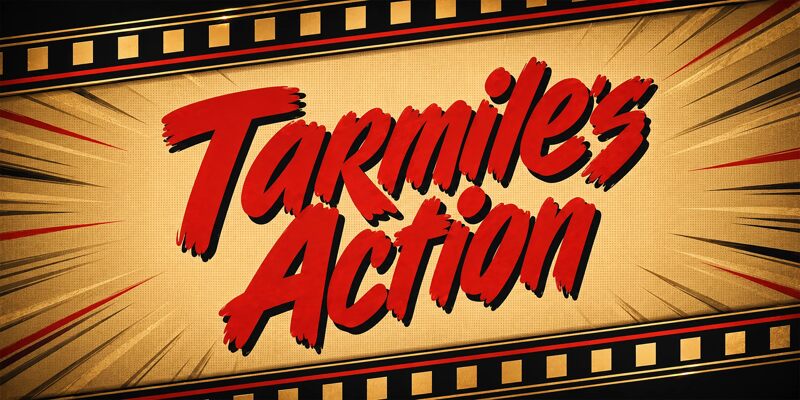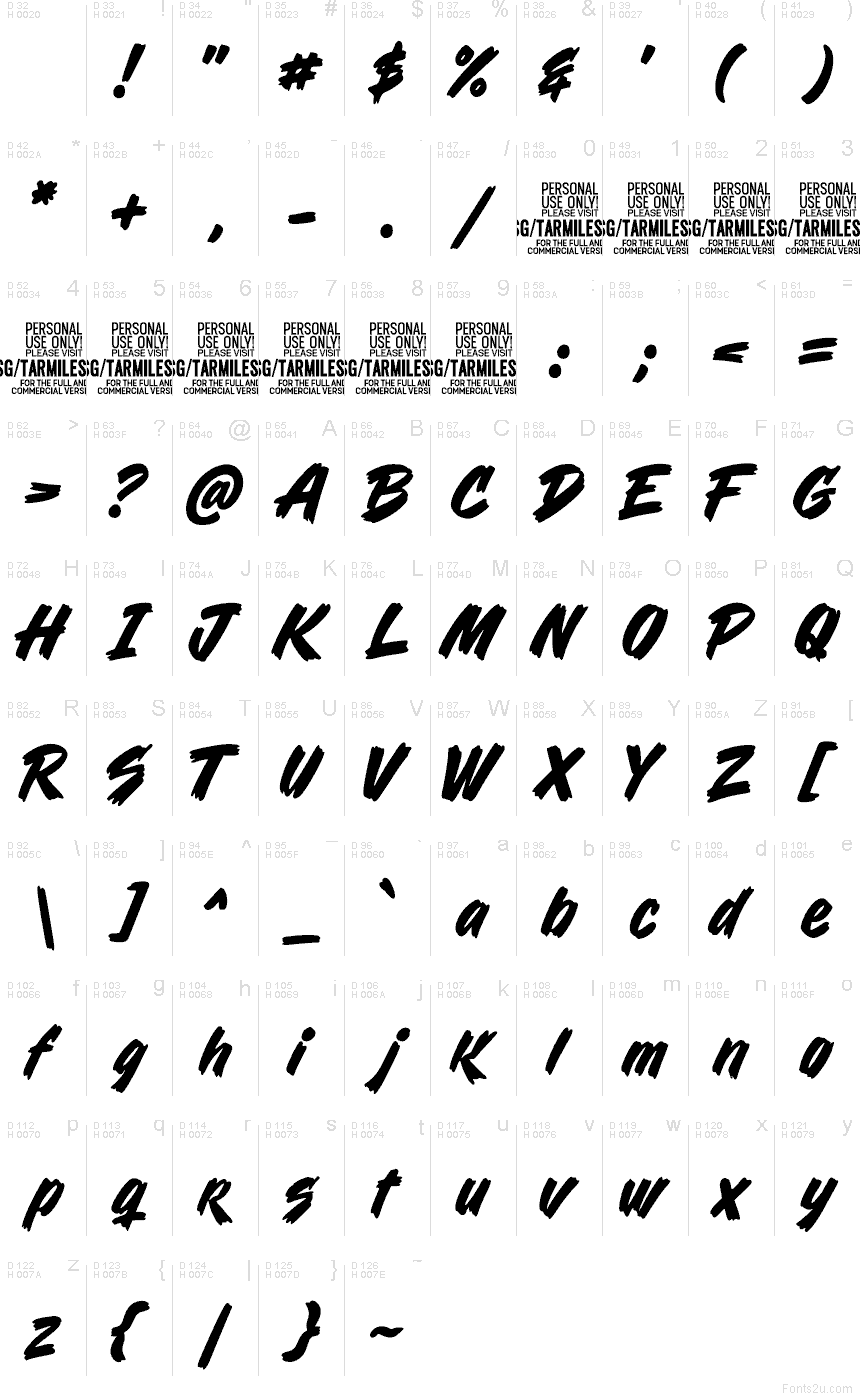
Tarmiles Action PERSONAL USE Regular
Tarmiles Action od Mansa Grebacka je bezplatné štetcové písmo s rýchlym, maliarskym švihom a drsným, ručne kresleným okrajom. Písmená sa k sebe nakláňajú v širokých, atramentových ťahoch, s ostrými zákrutami a skrátenými koncami, vďaka čomu pôsobí celé písmo svižne, výrazne a trochu nepokojne.
Hodí sa na hudobné vizuály, streetwearové značky, plagátové nadpisy, nálepky na nápoje a titulné karty, kde hľadáte skôr pohyb než uhladenosť. Ako bezplatné písmo sa hodí aj na texty na obaloch alebo krátke slová v štýle loga, pretože hustý štetcový rytmus a tesné spoje dodávajú aj krátkym frázam dojem jedného maliarskeho gesta.